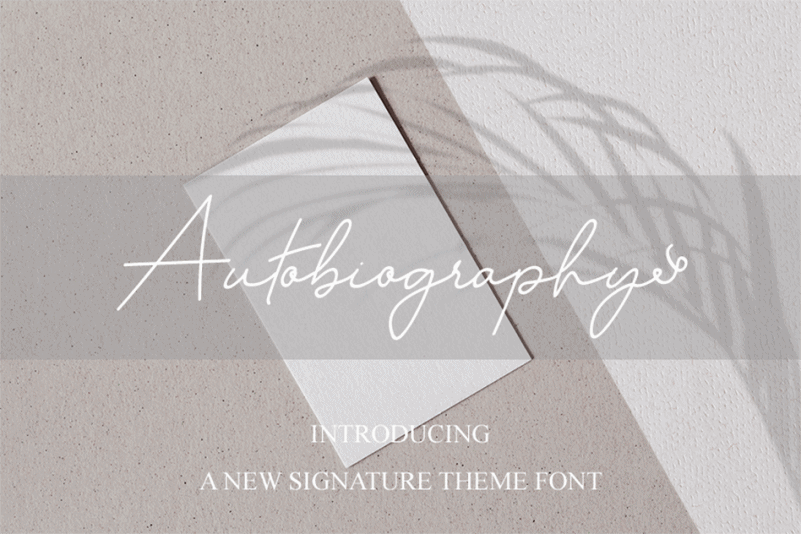
Autobiography Handwritten Font – Fonte Grátis
Autobiography Handwritten Font
Autobiography Handwritten Font é uma fonte escrita à mão que transmite um toque pessoal e sofisticado para quem a usa. Com linhas perfeitamente detalhadas e harmoniosas, ela se destaca como uma escolha inconfundível para os amantes de gráficos criativos. Esta fonte é ideal tanto para designers digitais quanto para estilistas de moda, oferecendo um toque elegante a qualquer projeto sem comprometer o caráter moderno e atual da Autobiography Handwritten Font. Combinar este tipo de estilo com outros recursos visuais certamente resultará em criações memoráveis e imprevisíveis. Seja no design de revistas, arquitetura ou marketing digital, esta fonte escrita à mão certamente vai se destacar, adicionando um toque personalizado que faz a diferença.